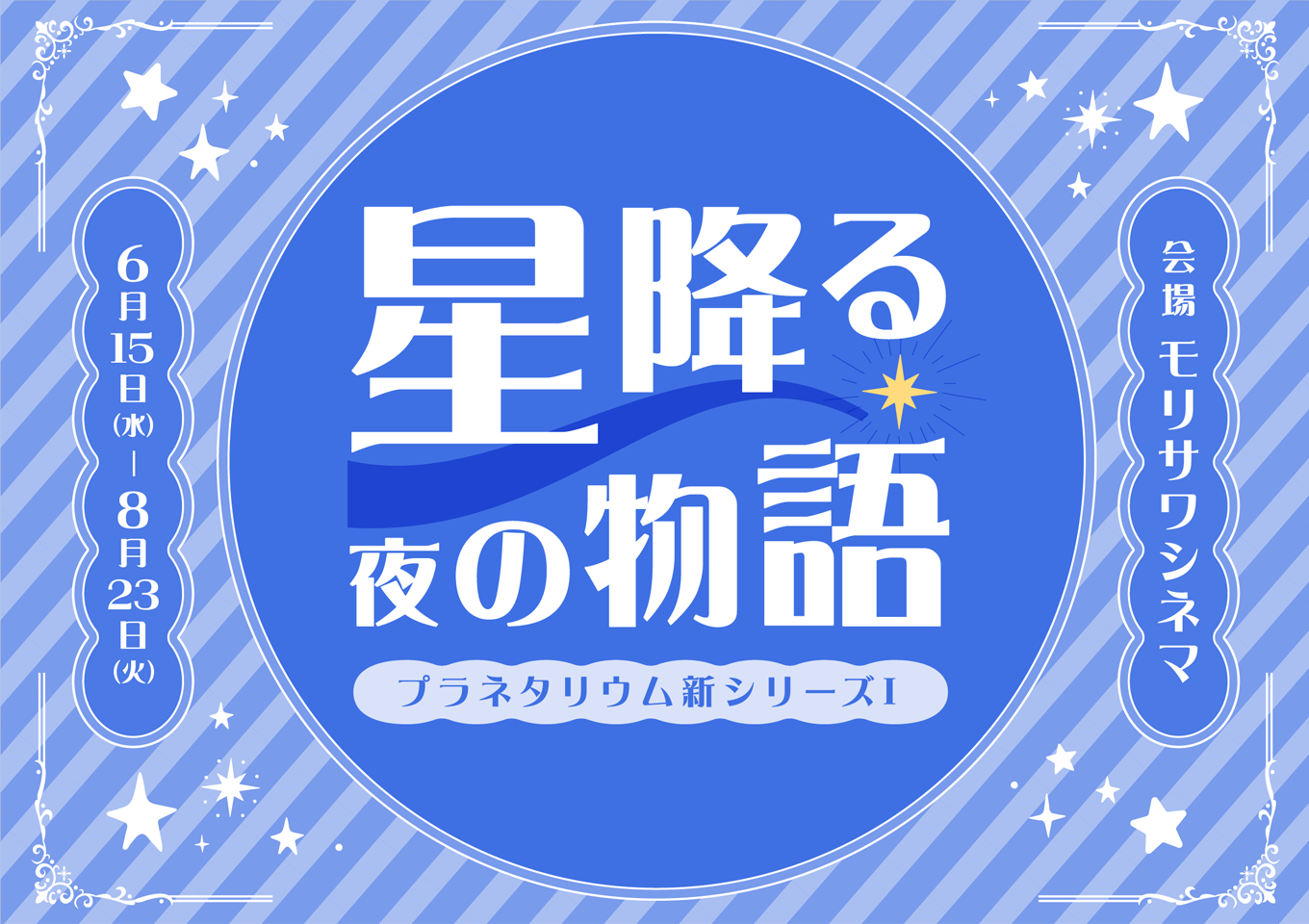
やや低めの重心をもつスクエアな骨格の漢字に、レトロモダンな印象のかなを合わせた、ハイコントラストなデザイン書体です。起筆・収筆にうろこのような装飾が施してあり、すっきりとした可愛らしさを演出します。広告や動画テロップなどで、ロゴのように打ち出したい際にも活用いただけます。なお本書体はモリサワで制作したかな・英数字に、Arphic Typesの「AR浪漫明朝体」の漢字を組み合わせています。